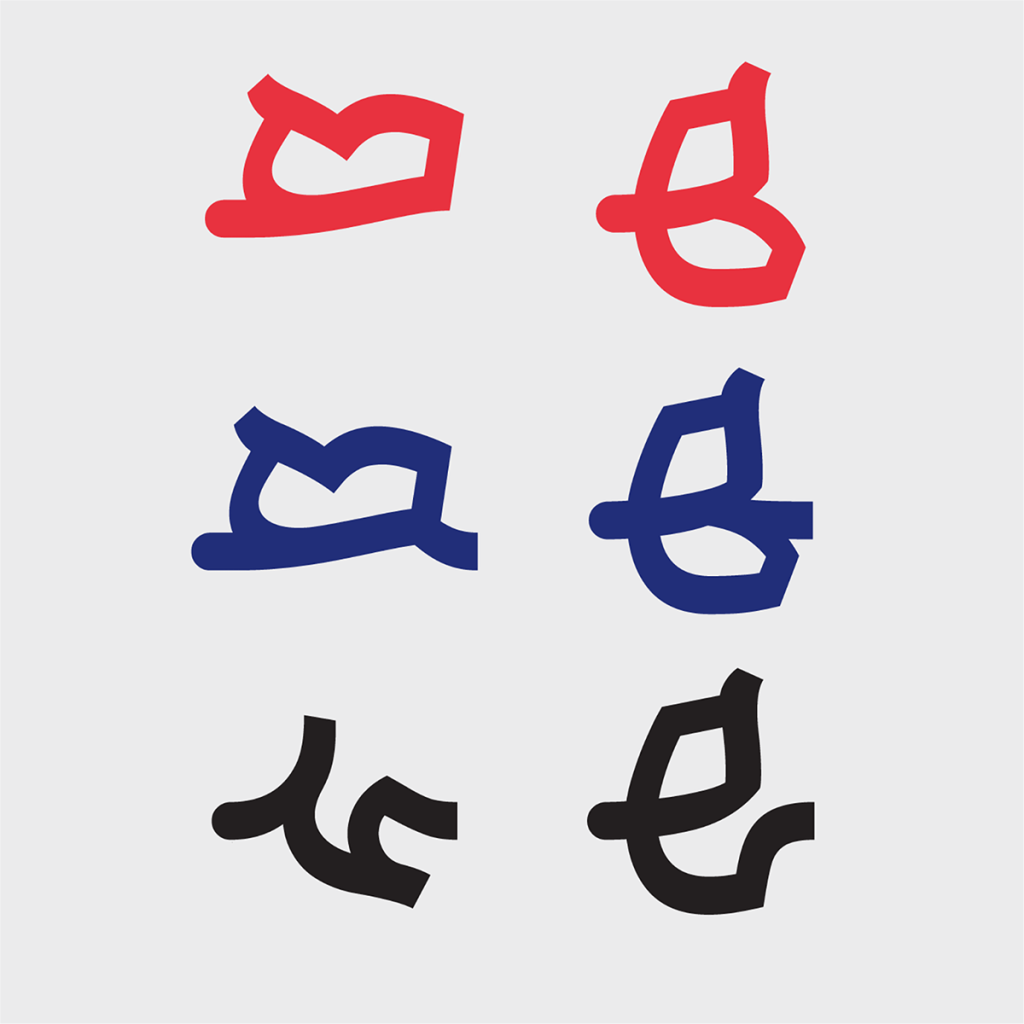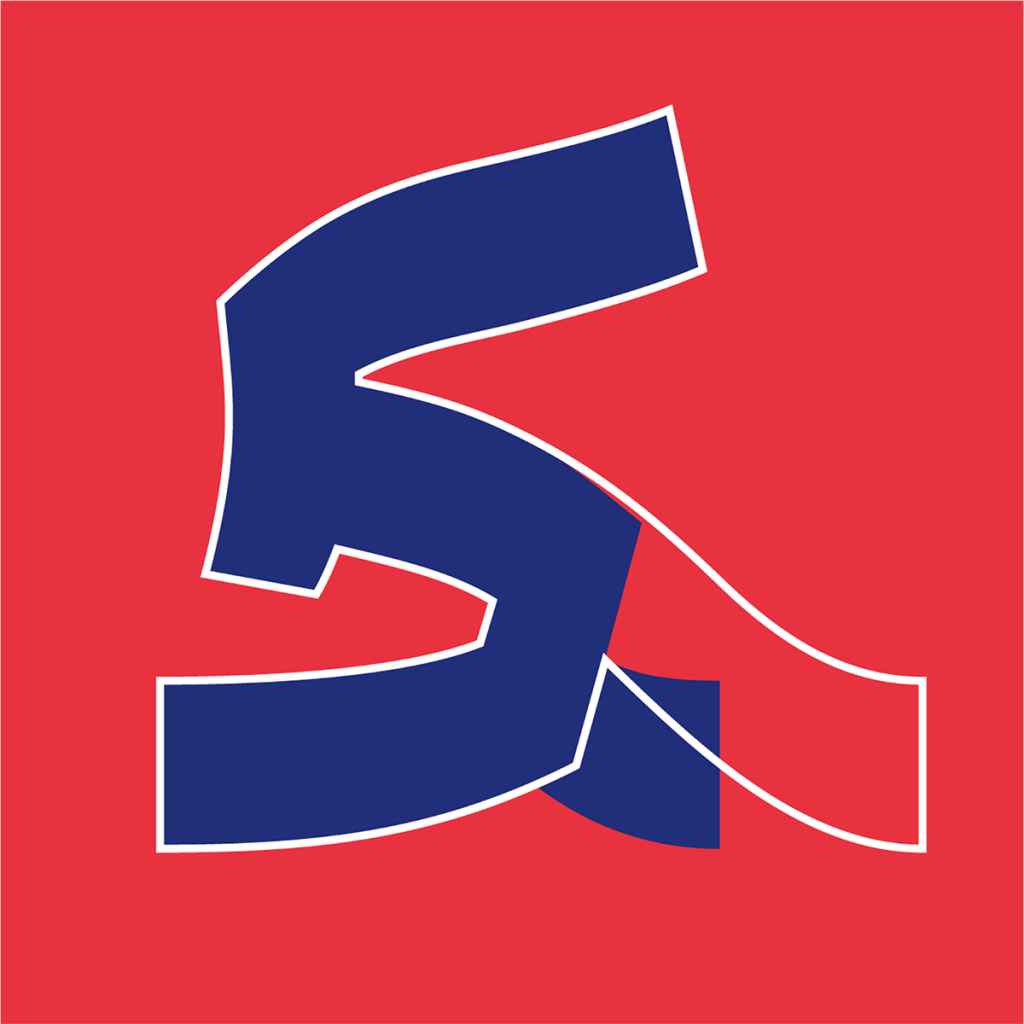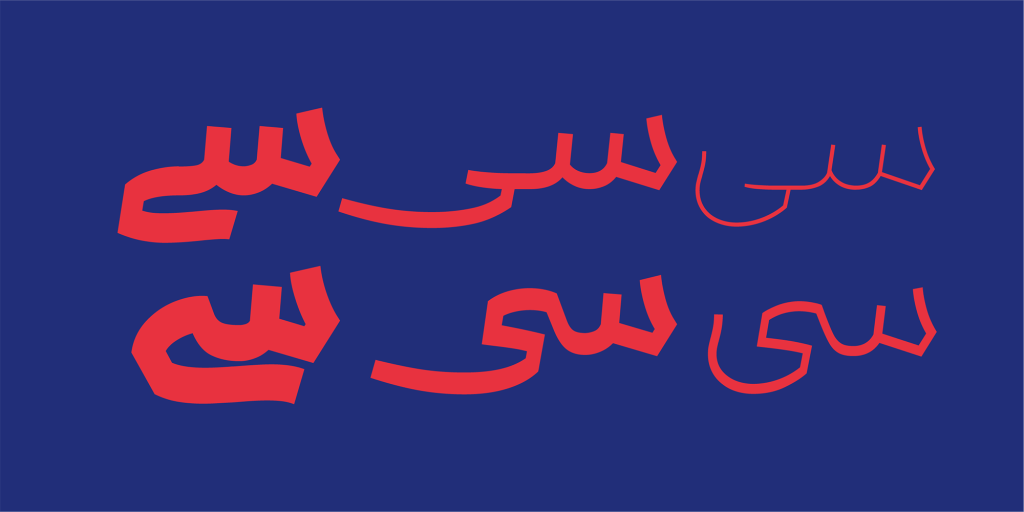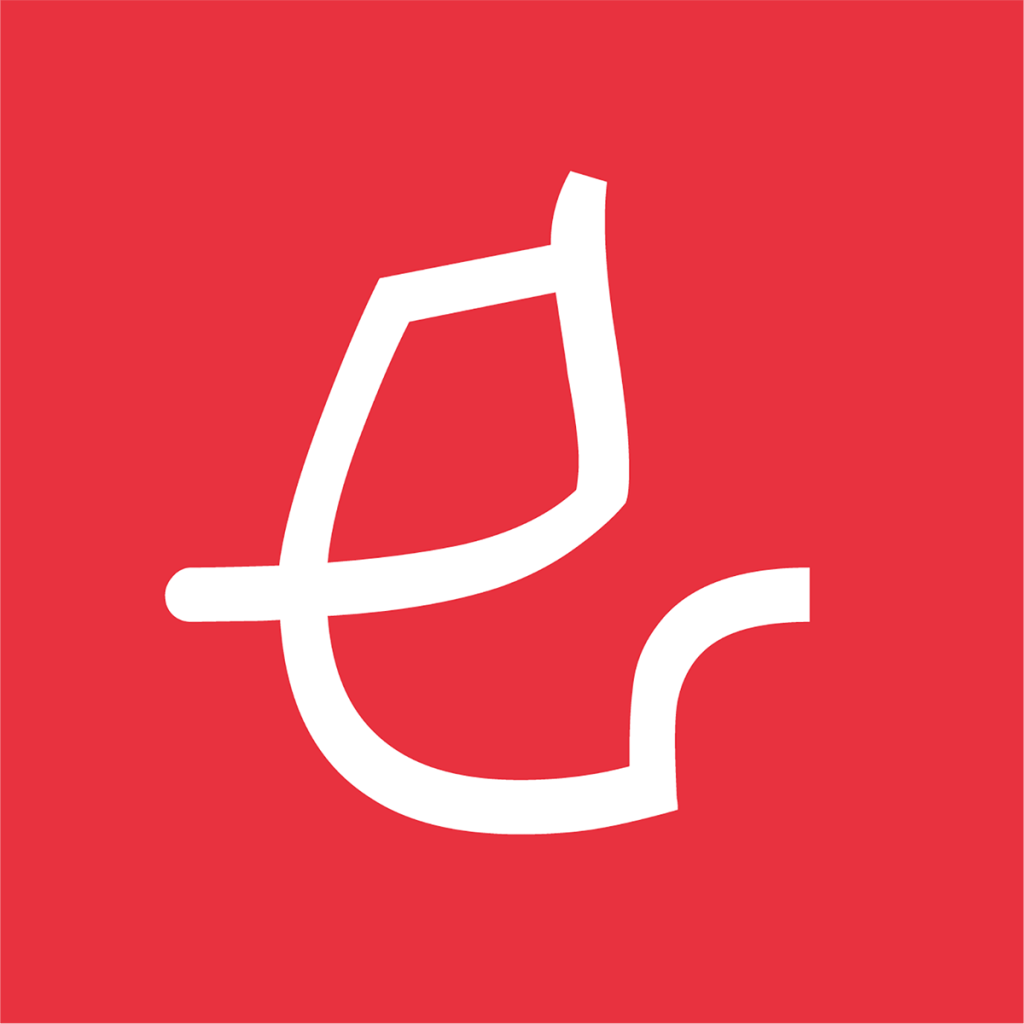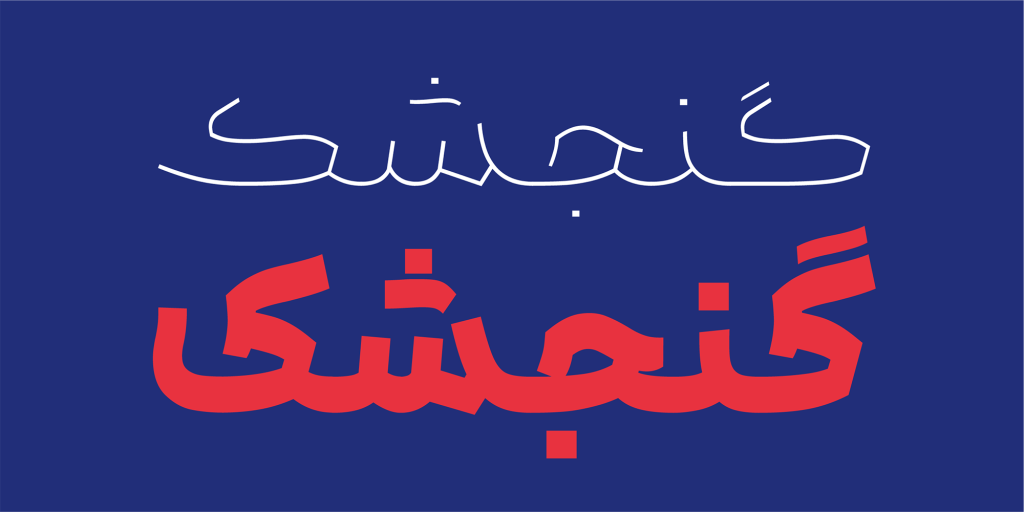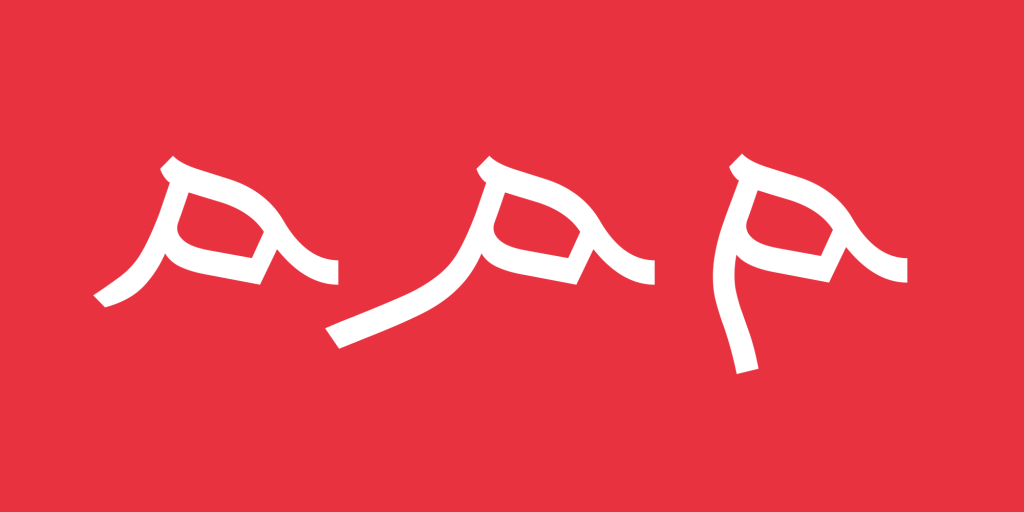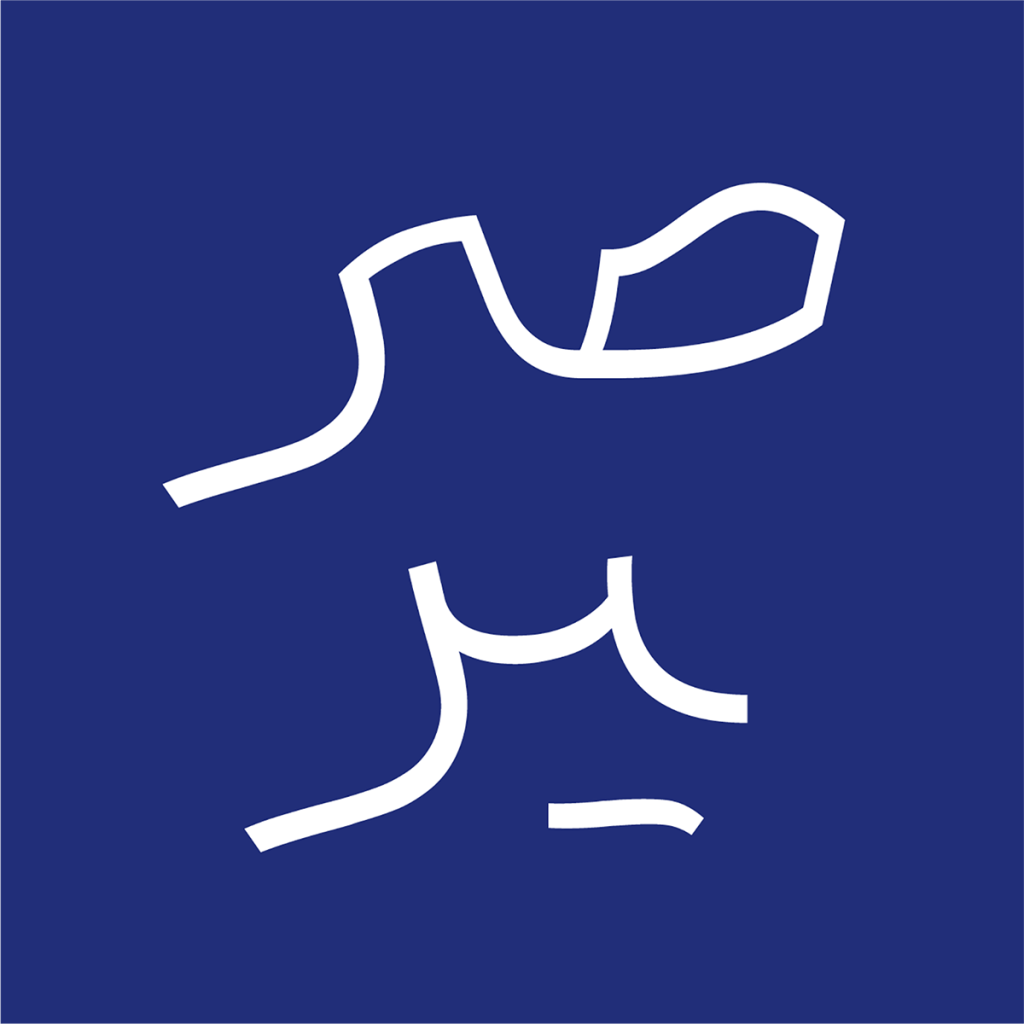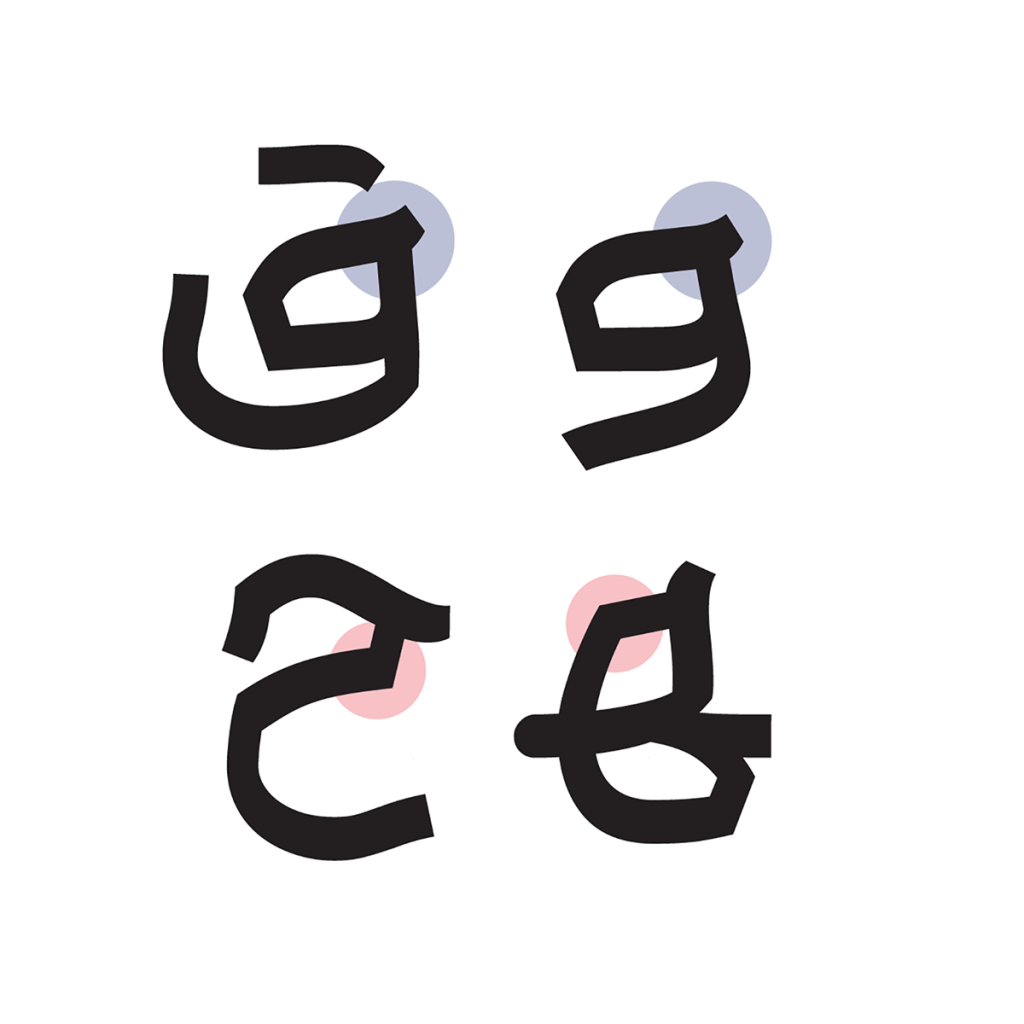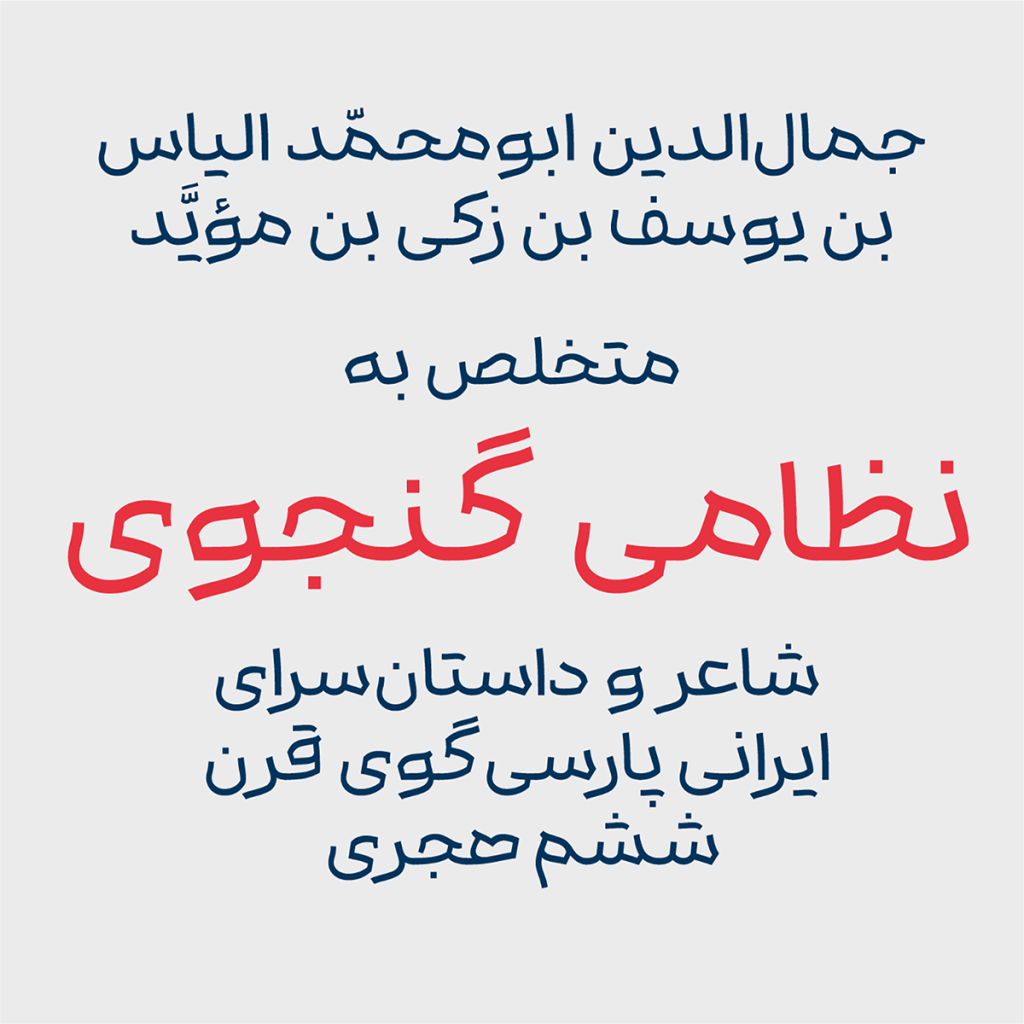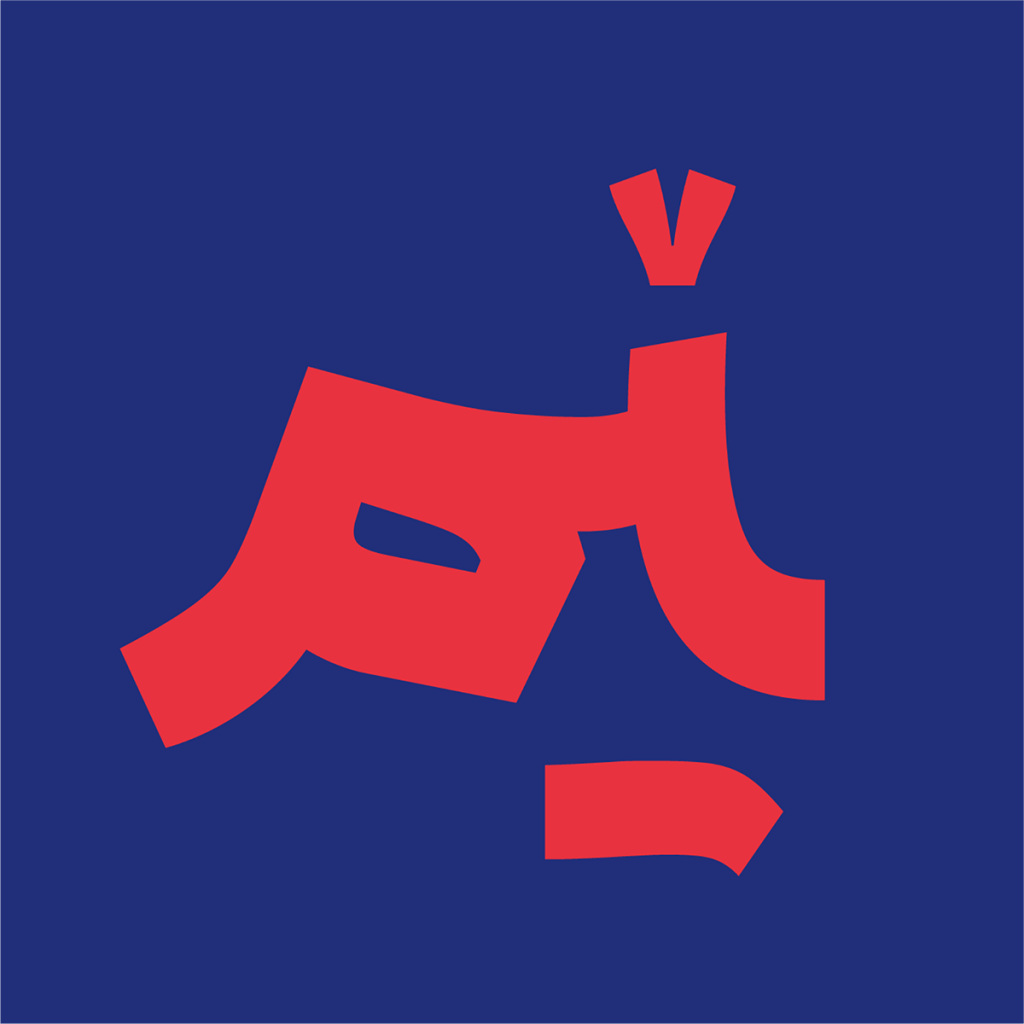
فونت باوان قلمی پرانرژی و شاد مناسب برای متون کوتاه و عناوین تبلیغاتی و… این قلم با شخصیت اکتیو فعالی که دارد مطمئنا نگاه ها را به خود جذب و از قدرت نمایشی بودن خود برای رفع نیازهای شما استفاده می کند.
فونت باوان قلمی امروزی و پر انرژی
فونت باوان الهام و اقتباس گرفته از ترکیب های مختلف از خطوط خوشنویسی است . اساس و شاکله اصلی این تایپ فیس از خانواده هندسی پیروی و تبعیت دارد ولی  از دو خط خوشنویسی  نسخ و ثلث هم ارث بری هایی را دارد. با دقت در فرم طراحی و ضخامت سطحی این تایپ فیس می توان دریافت که ضخامت آن یکسان و از دسته تایپ فیس های منولاین است.
همانطور که پیش تر نیز اشاره شد این قلم به واسطه فرم طراحی خاص آن ارتباطی نزدیک و صمیمانه با مخاطب برقرار می کند و دارای ویژگی نمایشی نسیتا بالایی است. کاربرد آن در متون کوتاه و عناوین می باشد. گزینه‌ای مناسب برای استفاده در تبلیغات، پست‌ها و استوری‌های شبکه‌های اجتماعی و همچنین بسته‌بندی محصولات مختلف تبدیل می‌کند.
راه مداوم و طولانی محال تا متولد شدن آن
باوان دارای حس و حال امروزی و نو می باشد . از ویژگی های این تایپ فیس زنده و پویا بودن آن است . از همین سبب با مخاطبین جوان دوست و همراه و مناسب فضاهای جدید و به روز است. از نقطه نظر ویژگی های گفته شده و همچنین هم خانوادگی فونت محال بسیار نزدیک به این قلم می باشد.
تنوع زبانی و وزنی تایپ فیس باوان
این قلم دارای خانواده ای از 6 وزن مختلف است تا نیاز های طراحی را برای شما در سطوح مختلف مرتفع نماید. همچنین با طراحی حروف و لیگچرهای زبان های مختلف از جمله فارسی، اردو ، عربی و کوردی می باشد. در تصاویر نمونه که برای شما دوستان قرار داده شده است می توانید این تنوع گسترده از زبان های مذکور را مشاهده کنید.
حروف و ترکیبات جایگزین (Discretionary Ligatures)
همه می دانیم که پشتیبانی از ویژگی ترکیبات و لیگچر های جایگزین علاوه بر زیبایی بخشیدن به طراحی سبب ایجاد تنوع و پویایی بیشتر و آزاد گذاشتن دست طراحان در انتخاب گلیف های متنوع برای به فعلیت رساندن ویژگی های گفته شده است. باوان نیز با بهره بردن از این ویژگی به شما عزیزان امکانات لازم را ارائه می دهد تا در نرم افزار های طراحی از جمله ایلسترتور و فتوشاپ پویایی و تنوع بیشتری به نوشته ها و طراحی های خود دهید.